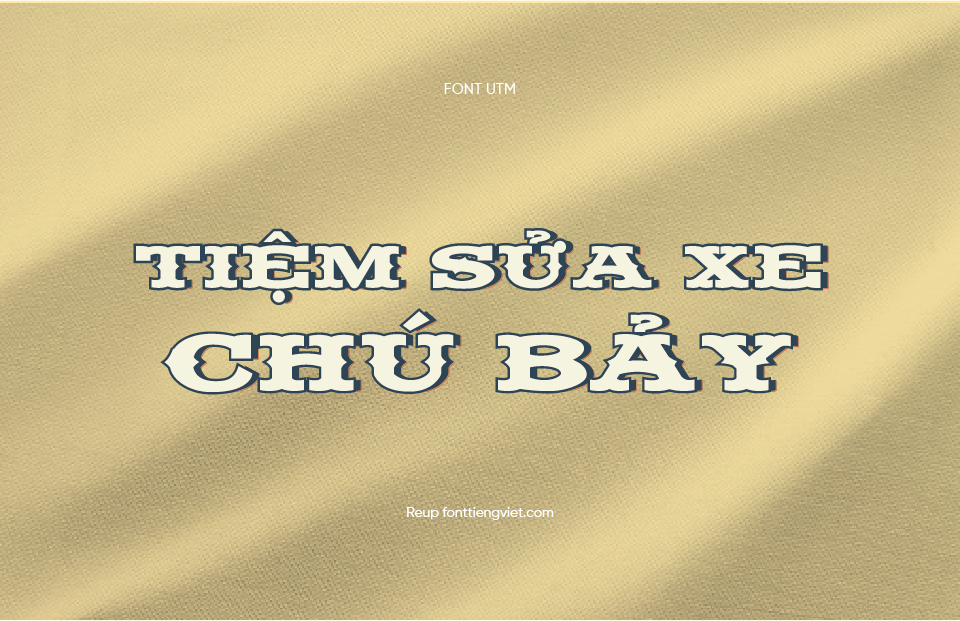
Font Việt hóa UTM Fancy Full
Giới thiệu về bộ Font Việt hóa UTM Fancy Full
Trong thế giới thiết kế đồ họa tại Việt Nam, việc tìm kiếm một bộ font chữ vừa đảm bảo tính thẩm mỹ, vừa hỗ trợ gõ tiếng Việt hoàn chỉnh là điều vô cùng quan trọng. Font Việt hóa UTM Fancy Full là một trong những bộ sưu tập nổi tiếng nhất, được cộng đồng thiết kế tin dùng nhờ sự đa dạng và linh hoạt. Đối với các bạn học sinh hay thầy cô giáo, việc sử dụng Font Miễn Phí chất lượng như UTM giúp bài thuyết trình và tài liệu học tập trở nên sinh động, chuyên nghiệp hơn rất nhiều.
Ưu điểm nổi bật của font UTM
Bộ font này bao gồm hàng trăm kiểu dáng khác nhau, từ những nét chữ viết tay mềm mại đến các định dạng serif cổ điển hay sans-serif hiện đại. Đặc biệt, bộ font này đã được tối ưu mã Unicode, giúp bạn không bao giờ gặp lỗi font khi gõ các dấu tiếng Việt phức tạp trên Word hay Photoshop.
Cách ứng dụng Font Việt hóa UTM Fancy Full trong học tập và công việc
Sử dụng Font Việt hóa UTM Fancy Full giúp nâng tầm các dự án sáng tạo. Bạn có thể dùng các font nghệ thuật để thiết kế bìa báo tường, thiệp mời sự kiện trường học hoặc làm nổi bật các tiêu đề quan trọng trong đồ án. Sự kết hợp giữa đường nét tinh tế và khả năng hiển thị rõ nét giúp người xem dễ dàng tiếp nhận thông tin.
Lưu ý khi sử dụng font chữ
Để đạt hiệu quả thị giác tốt nhất, bạn nên phối hợp giữa các font chữ có chân và không chân một cách hài hòa. Đừng quên kiểm tra kích thước chữ để đảm bảo tính dễ đọc trên các thiết bị khác nhau.
Kết luận về trải nghiệm Font Việt hóa UTM Fancy Full